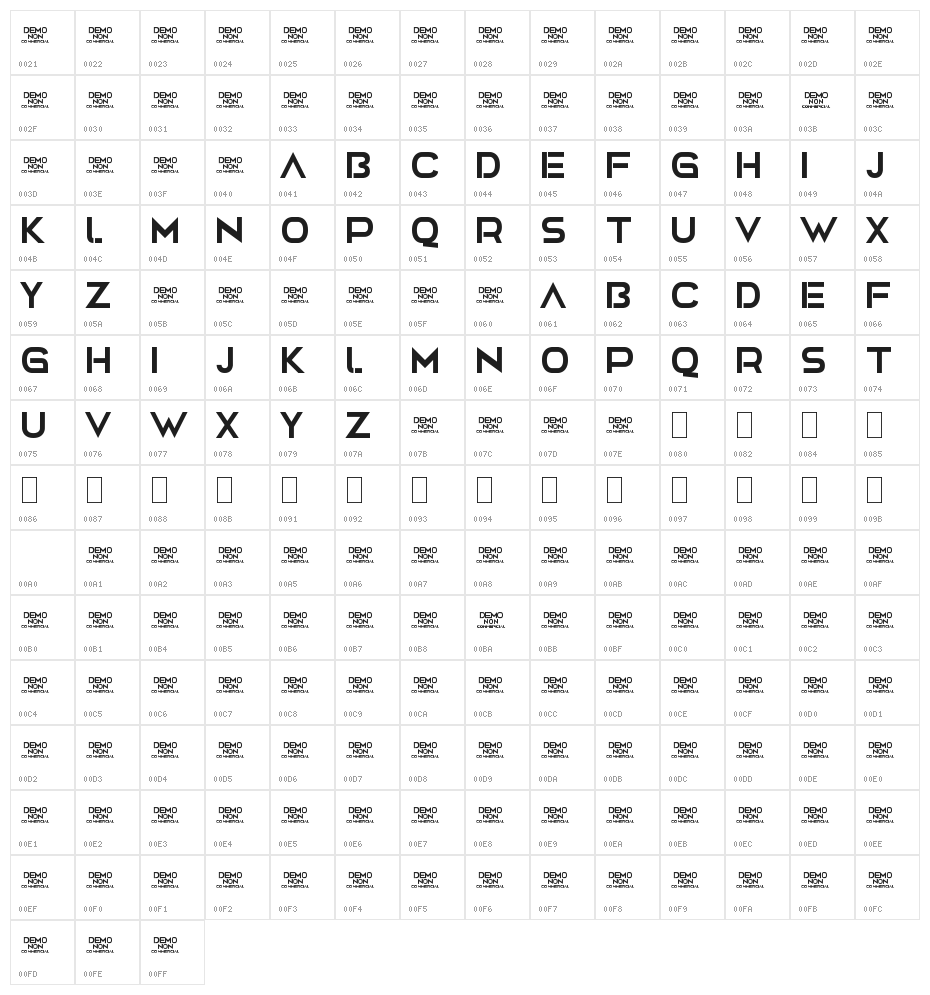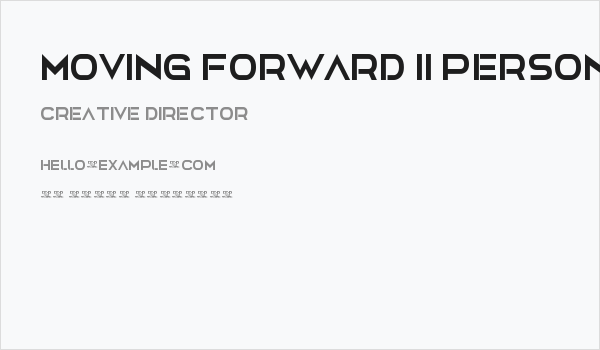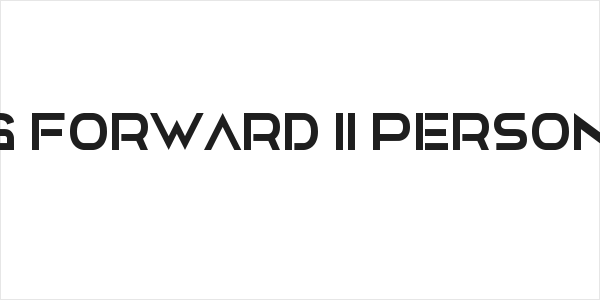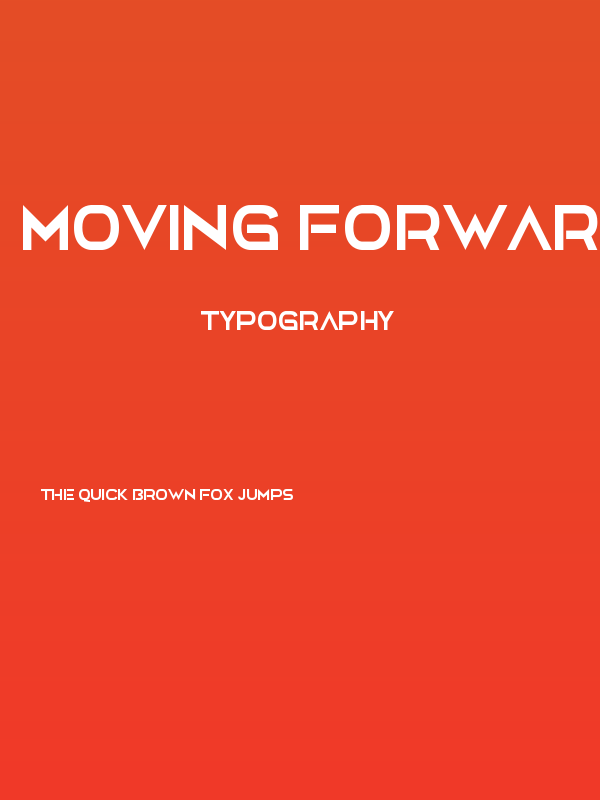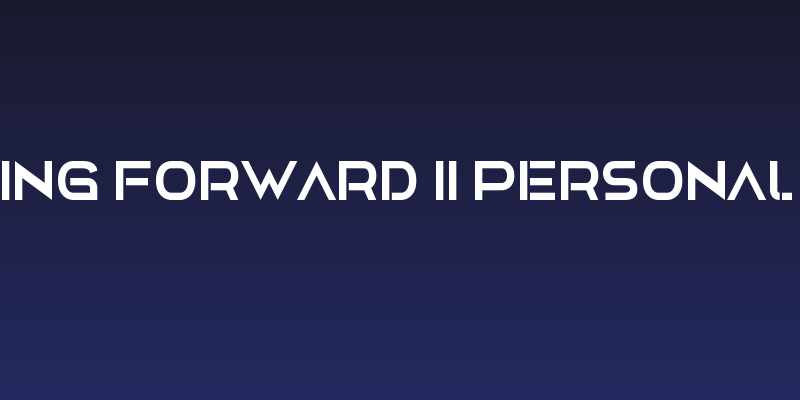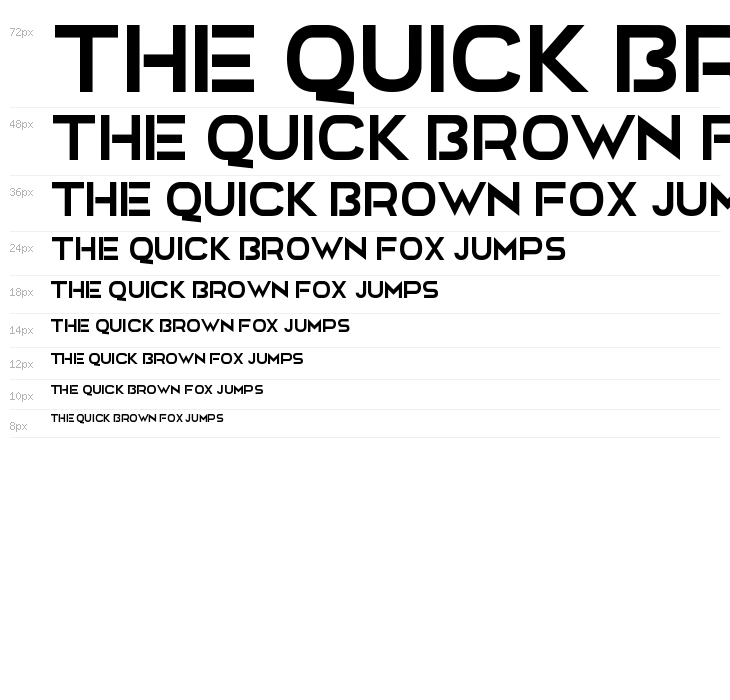
Moving Forward II Personal Use Font
| Progetti proposti | Ideal for technology branding, sci-fi themed projects, modern advertising, and innovative product packaging. |